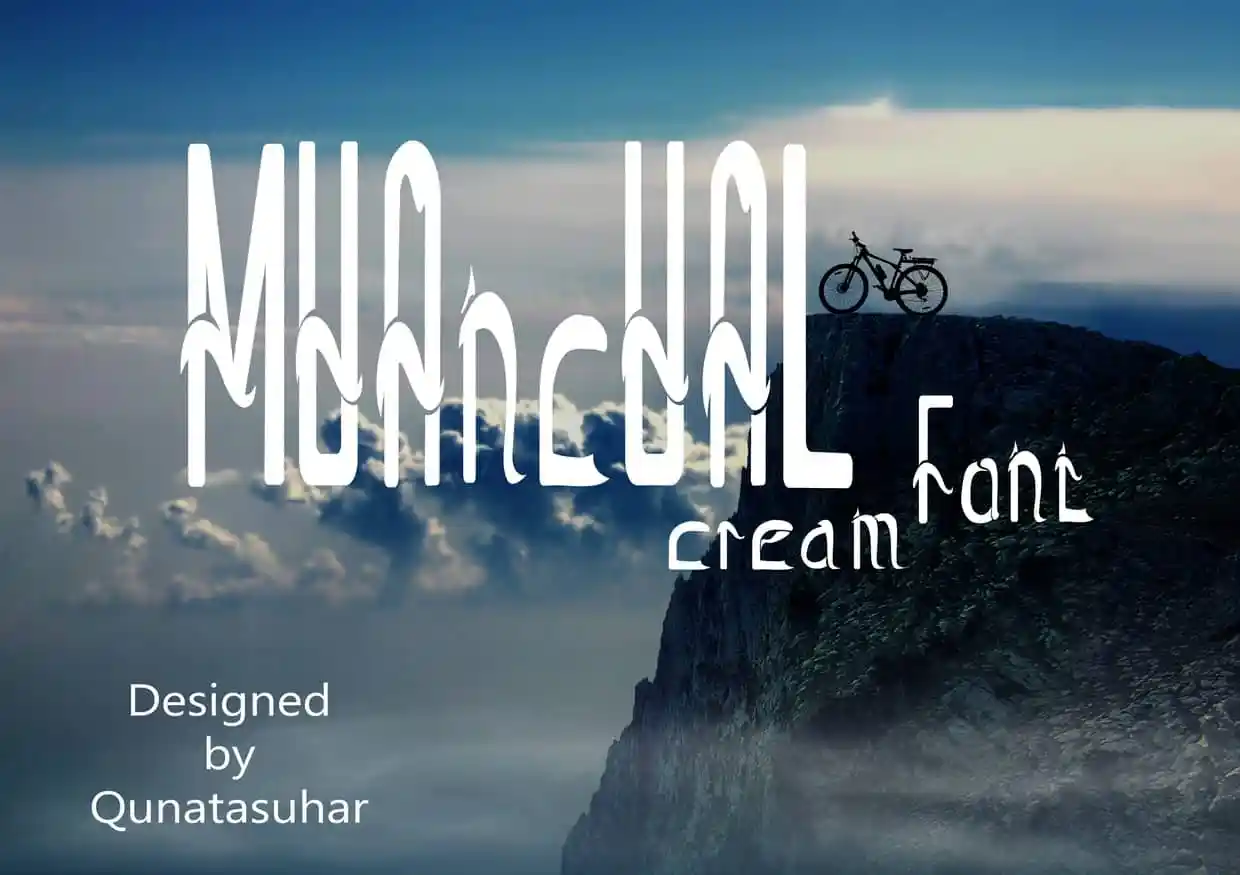
Aqui está uma descrição em português para a página de download da font ‘Muancual Font’, que segue as regras estabelecidas: “Descubra e baixe nossa nova fonte ‘Muancual’ da categoria Sans Serif, criada pelo designer qynata suhar. Com um design limpo e moderno, esta fonte é perfeita para aplicativos digitais, sites ou qualquer projeto que desejávamos uma aparência minimalista. Aqui você terá a oportunidade de baixar gratuitamente a font ‘Muancual’ em seu dispositivo. Após o download, você poderá começar a usar a nova fonte imediatamente e compartilhar suas criações com outros designers ou usuários da web que possam gostar dessa novidade. Com seus traços finos e linhas retas, a font ‘Muancual’ é ideal para criar gráficos visuais simples e eficientes. Perfeita para aplicativos de design editorial, sites pessoais ou qualquer projeto em desenvolvimento, esta fonte oferece um toque moderno sem comprometer a legibilidade. Com o uso desta fonte, você adquire uma ferramenta versátil que pode ser usada em vários contextos, permitindo-lhe criar interfaces de usuário atraentes e layouts visuais modernos. Não perca mais tempo buscando por opções para seus projetos digitais; ‘Muancual’ está aqui para tornar o seu trabalho mais rápido e eficiente.”
Designer: qynata suhar